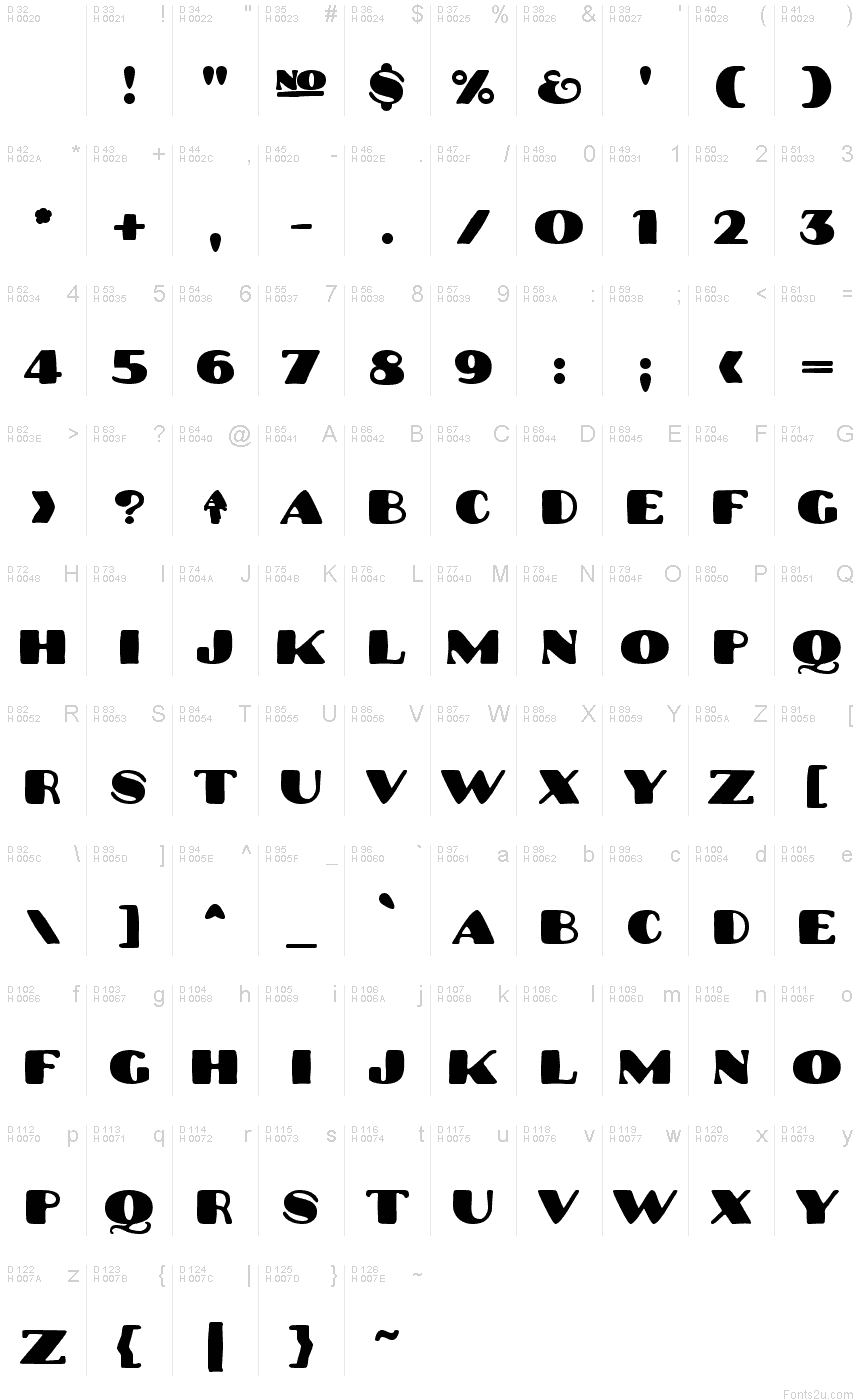
Platinum Hub Caps Solid
Platinum Hub Caps Solid autorstwa R. Gast to darmowy, retro krój displayowy, który oddaje miękki, obły charakter napisów na vanach i plakatowych alfabetów z końca lat 60. Litery są ciężkie i zaokrąglone, z szerokimi, blokowymi szczytami, zwężonymi krzywiznami i lekko ręcznym wykończeniem, dzięki czemu ta wyrazista sylwetka nie wydaje się sztywna.
Świetnie sprawdza się na okładkach albumów, oznaczeniach marek garażowych, ulotkach eventowych, kartach tytułowych i krótkich nagłówkach na opakowaniach, gdzie potrzeba mocnego, vintage’owego brzmienia. Jako darmowy font, szczególnie dobrze nadaje się do monogramów, dużych inicjałów i szkiców logo, ponieważ litery mają wystarczającą wagę i charakter, by utrzymać kompozycję bez dodatkowych ozdobników.